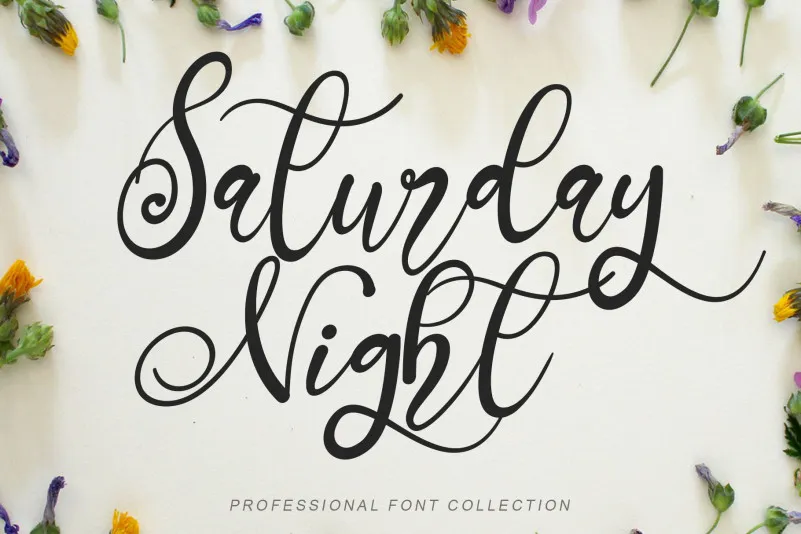
Essa é uma fonte script elegante e fluida feita à mão. Ela mantém seus traços clássicos da caligrafia enquanto oferece uma sensação contemporânea e atualizada. Esta fonte traz um ar de sofisticação, mas também convida a experimentar algo novo e interessante. Se você está procurando por uma maneira única para dar vida aos seus projetos digitais, este é o caminho. Aqui no ‘Saturday Night Font’, você encontrará mais opções criativas que vão além da usual em busca de um estilo único.